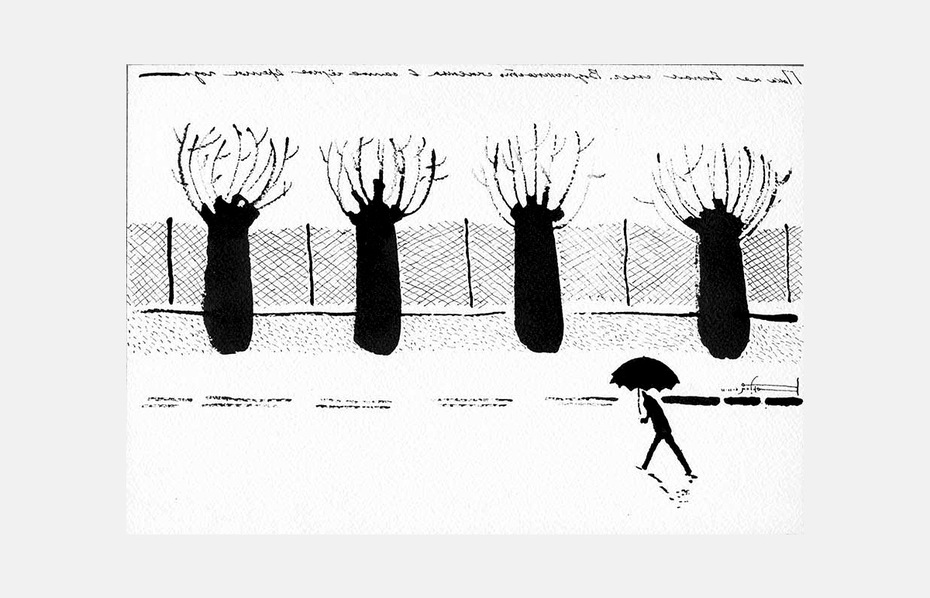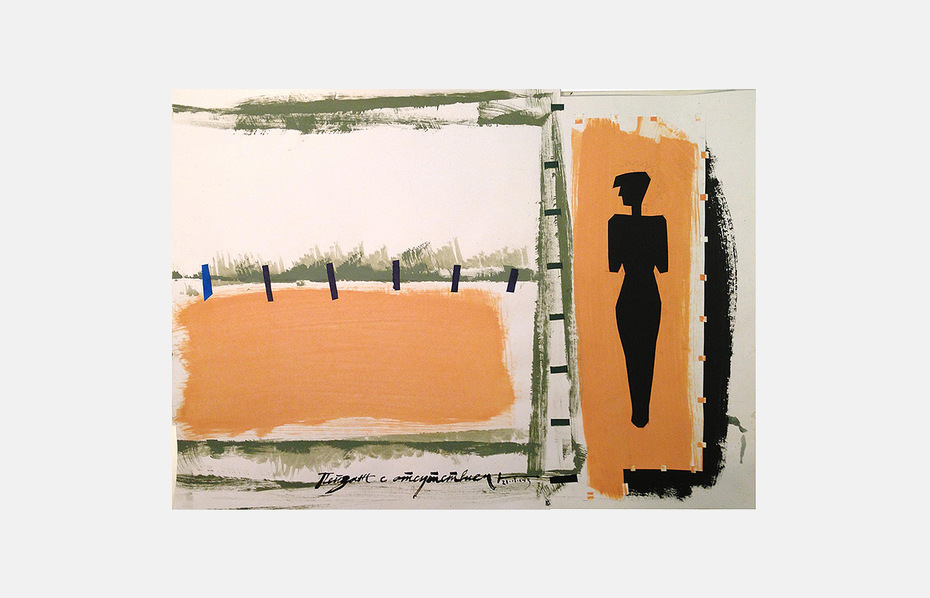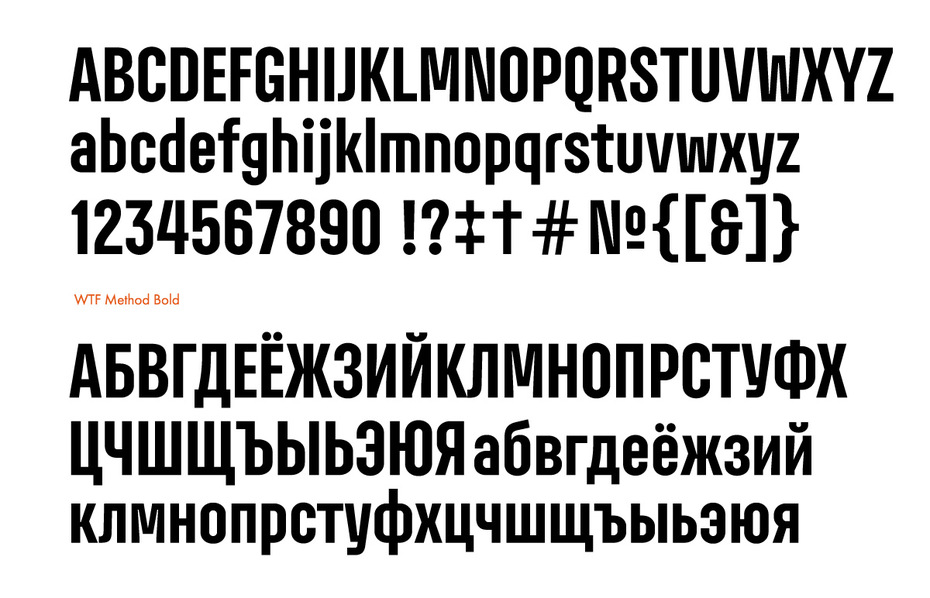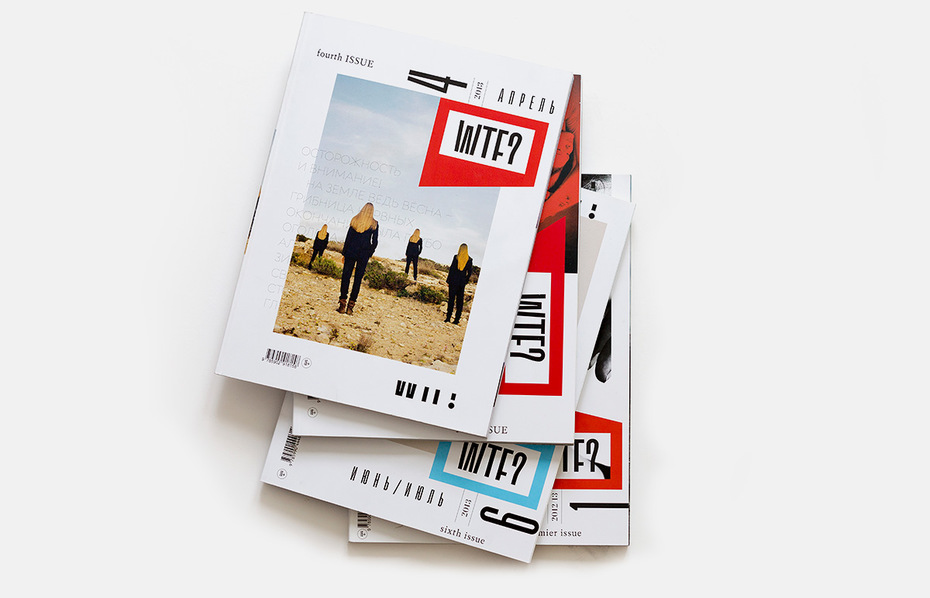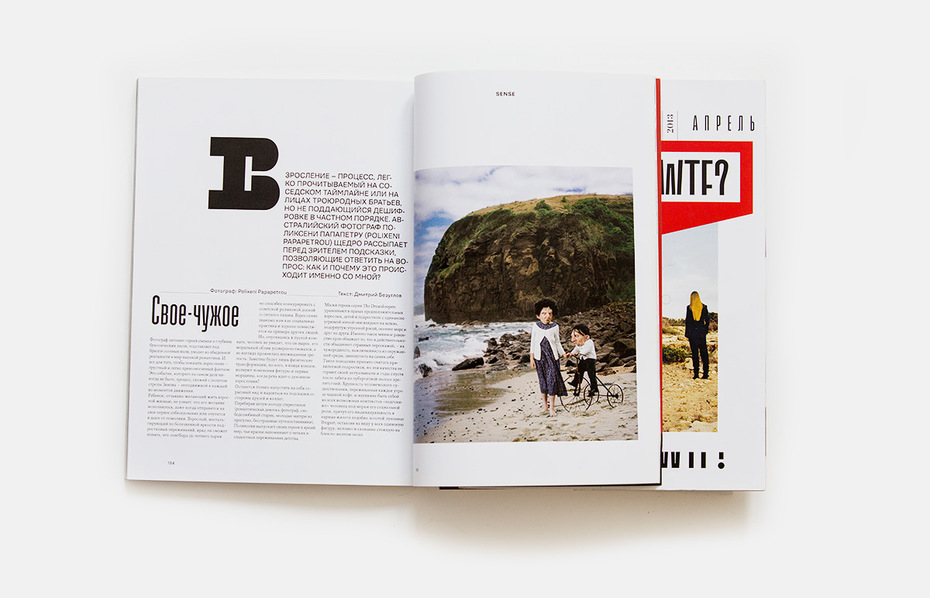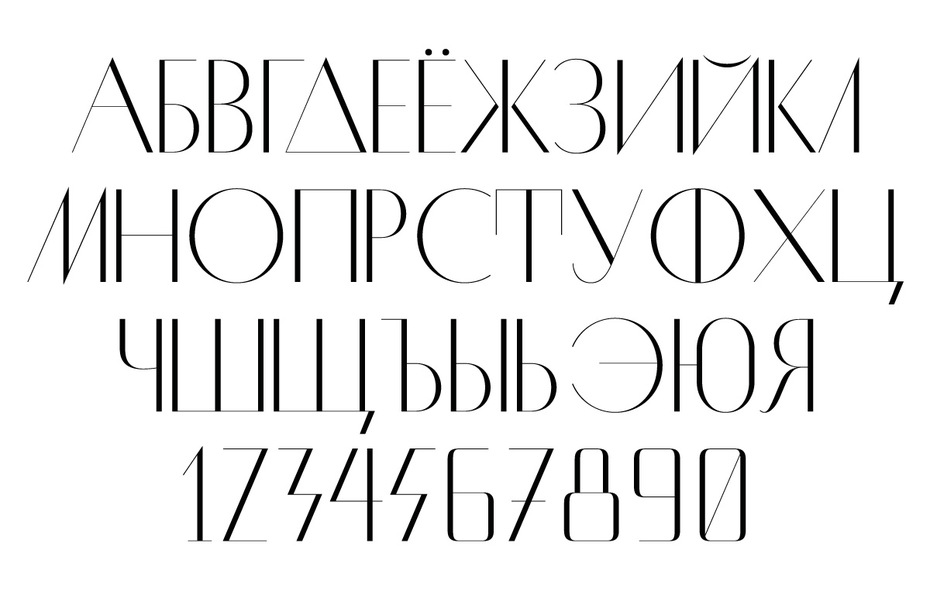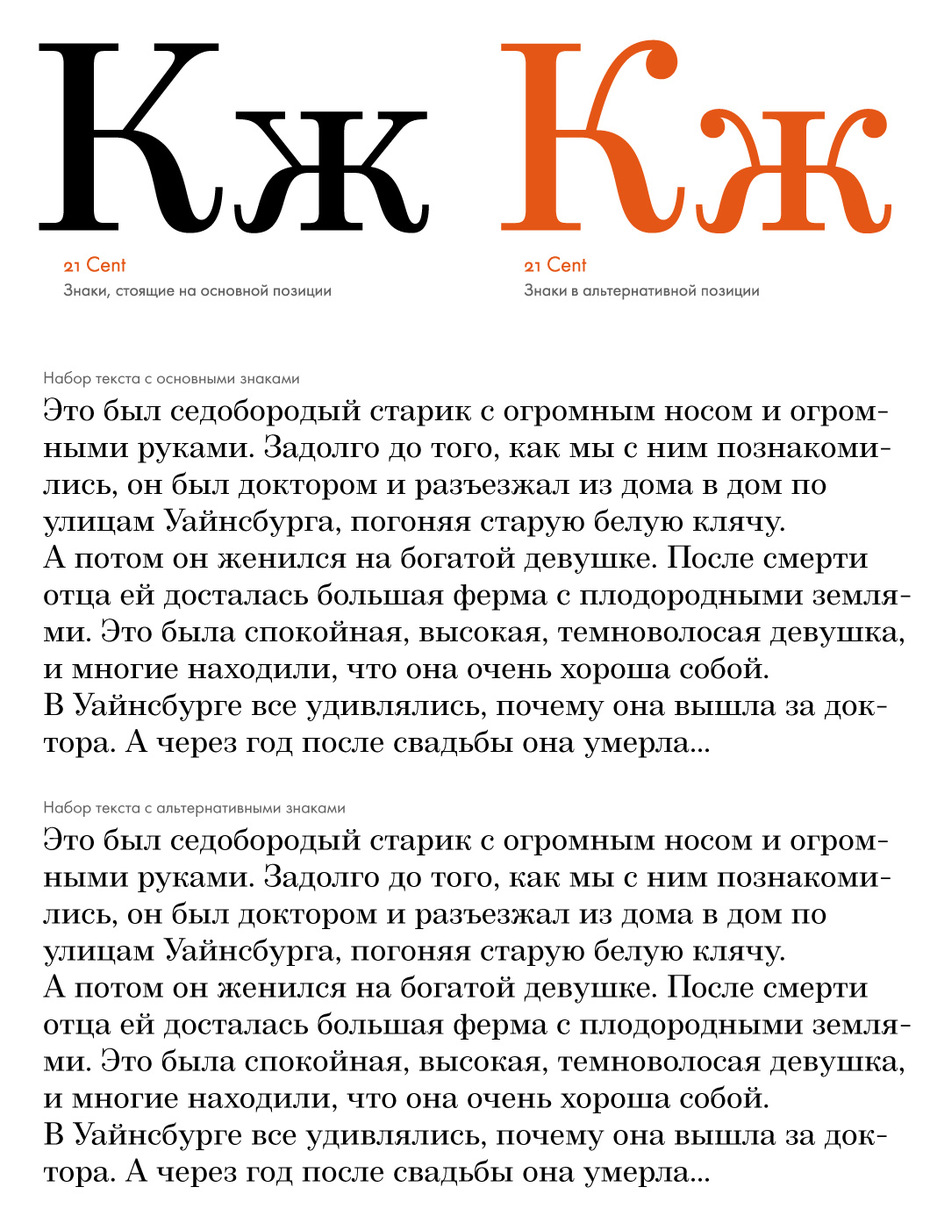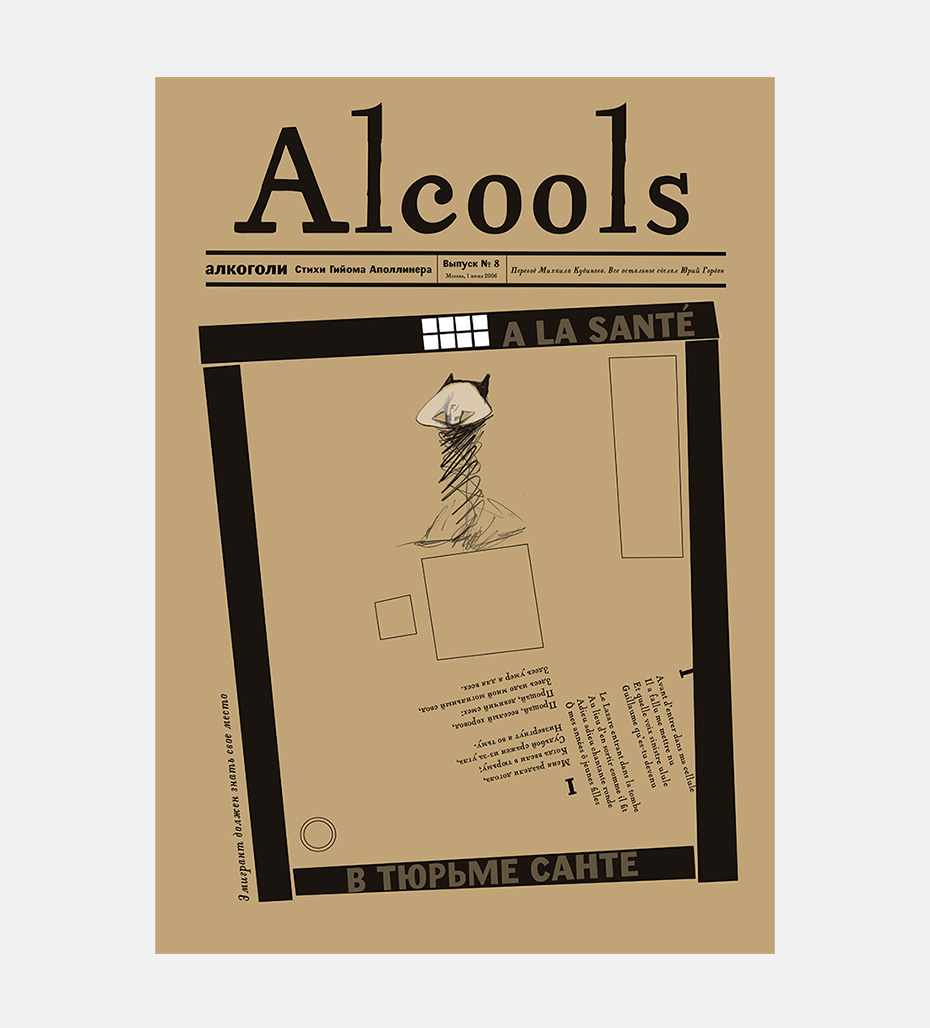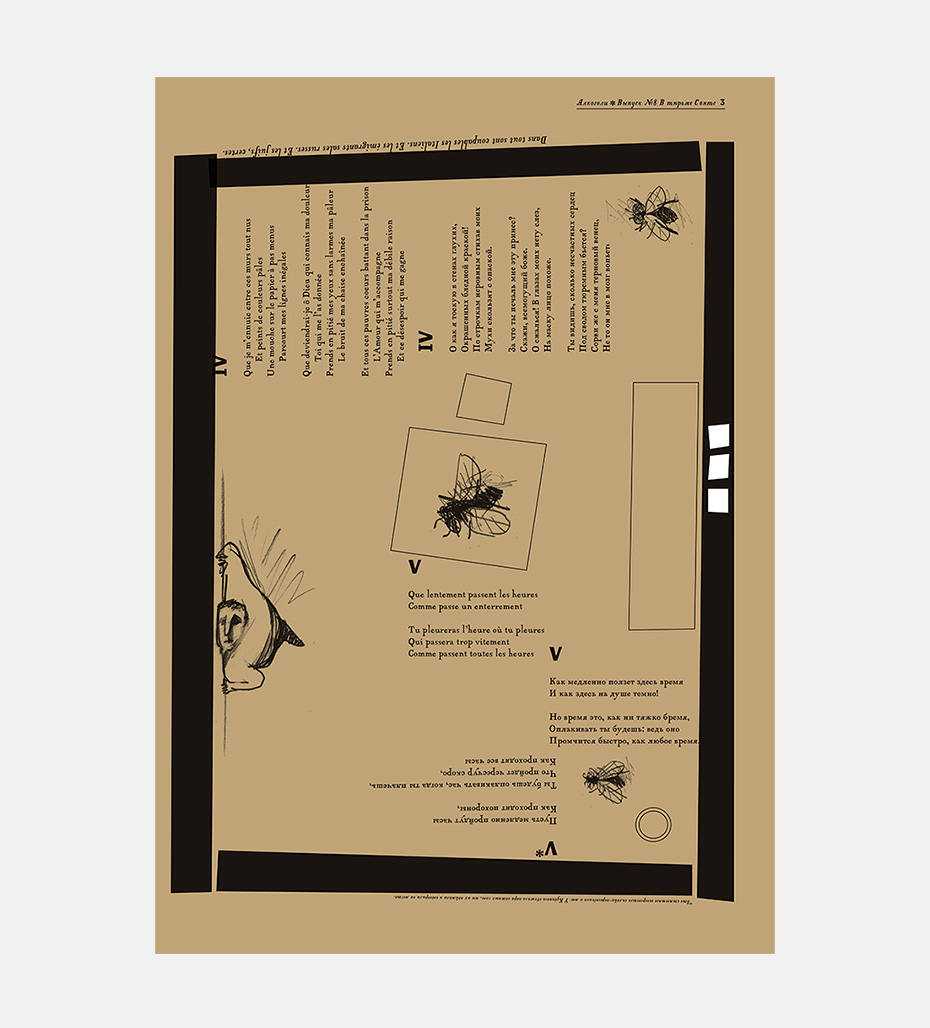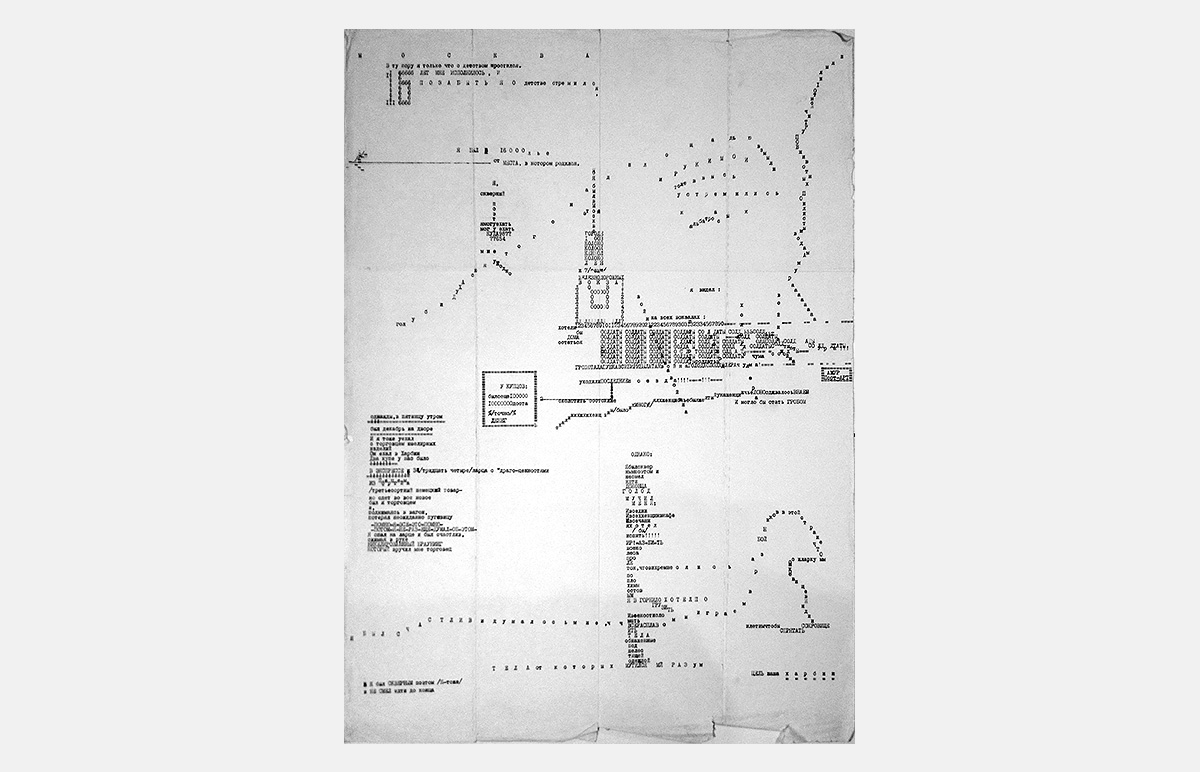
Самая маленькая из больших студий
ет­тер­хед — преж­де все­го сту­дия гра­фи­че­ско­го ди­зай­на, но от­ли­ча­ет­ся она тем, что по­чти во всех про­ек­тах ис­поль­зу­ет шриф­ты из соб­ствен­ной биб­лио­те­ки. А если под­хо­дя­ще­го шриф­та нет, то раз­ра­ба­ты­ва­ет его, ис­хо­дя из по­став­лен­ной за­да­чи. За го­ды ра­бо­ты «натуральное хозяйство» лет­тер­хе­дов об­ре­ло мас­шта­бы боль­шой шриф­то­вой биб­лио­те­ки с гар­ни­ту­ра­ми са­мых раз­лич­ных жан­ров — от ­ак­ци­дент­ных до тек­сто­вых. Хо­те­ли они то­го или нет, но Юрий Гор­дон и Ва­ле­рий Го­лы­жен­ков (не за­бу­дем так­же Оль­гу Ва­силь­ко­ву и Ил­ла­ри­о­на Гор­до­на) по­да­ли при­мер то­го, как при по­мо­щи до­ступ­ных всем тех­но­ло­гий мож­но со­здать яс­ный и уз­на­ва­е­мый ти­по­гра­фи­че­ский стиль, вби­ра­ю­щий в се­бя как тра­ди­ци­он­ные чер­ты, так и аб­со­лют­но но­ва­тор­ские об­ра­зы. И не толь­ко в об­ла­сти шриф­та, как мож­но убе­дить­ся, про­чи­тав ин­тер­вью.
Не­дав­но мы с удив­ле­ни­ем об­на­ру­жи­ли, что да­ле­ко не все рос­сий­ские гра­фи­че­ские ди­зай­не­ры зна­ют о сту­дии Letterhead. Это стран­но для та­ких ста­ро­жи­лов, да­же, мож­но ска­зать, пи­о­не­ров, как вы.
Ва­ле­рий Го­лы­жен­ков: А что в этом уди­ви­тель­но­го? Сей­час ин­фор­ма­ци­он­ный по­ток о ди­зай­не на­столь­ко ве­лик, что ед­ва хва­та­ет сил, что­бы сле­дить за те­ми, кто ра­бо­та­ет ря­дом с то­бой. Год прош­лый, год бу­ду­щий — вот вре­мен­ные рам­ки ди­зай­нер­ской па­мя­ти се­го­дня.
Юрий Гор­дон: Но ко­гда че­ло­век за­ка­зы­ва­ет ди­зайн, мар­ка всё рав­но важ­на. Кли­ен­ты-то зна­ют, к ко­му об­ра­ща­ют­ся и ко­го ре­ко­мен­ду­ют друг дру­гу. Но это от­дель­ный мир, ко­то­рый не пе­ре­се­ка­ет­ся с тем, о ко­то­ром мы го­во­рим.
Ва­ле­рий: Я дол­жен ска­зать, что и мы ма­ло что зна­ем. Но­вые ди­зайн-сту­дии, ге­рои, име­на — это нуж­но по­сто­ян­но от­сле­жи­вать, а еди­но­го ис­точ­ни­ка ин­фор­ма­ции, ко­то­рый бы и фор­ми­ро­вал сре­ду, и ин­фор­ми­ро­вал её, не су­ще­ству­ет. Что-то на­хо­дишь в фейс­бу­ке, что-то поз­во­ля­ет ви­деть пре­по­да­ва­тель­ская ра­бо­та... Прав­да, всё ча­ще хо­чет­ся не ис­кать но­во­го, а, на­про­тив, убе­речь­ся от шква­ла ин­фор­ма­ции, за­крыть­ся и знать как мож­но мень­ше.
По­лу­ча­ет­ся, что вид­ны и за­мет­ны се­го­дня те, кто гром­че осталь­ных, те, кто уме­ет со­зда­вать во­круг се­бя ин­фор­ма­ци­он­ную вол­ну. Это зна­чит для прак­ти­ку­ю­ще­го ди­зай­не­ра, что нуж­но по­сто­ян­но быть в фор­ме, на ви­ду?
Ва­ле­рий: Я ду­маю, что че­ло­век, до­стиг­ший вер­ши­ны в своём де­ле, по­доб­но вос­точ­ной тра­ди­ции, дол­жен за­бы­вать своё имя, брать дру­гое и на­чи­нать всё с ну­ля в но­вом сти­ле. Если он вдруг чув­ству­ет, что на­хо­дит­ся на вер­ши­не, в «то­пе», то дол­жен во­вре­мя со все­ми по­про­щать­ся, об­нять­ся и ска­зать: всё, ре­бя­та, до сви­да­ния. Ко­неч­но, в ди­зай­не все­гда есть свой «Рол­линг Сто­унз». Да, на За­па­де мож­но най­ти ин­те­рес­ных лю­дей и их про­ек­ты. И да­же уди­ви­тель­но, что эти лю­ди по-преж­не­му вы­да­ют со­вре­мен­ный про­дукт, со­звуч­ный на­стро­е­ни­ям, тен­ден­ци­ям. Про­дукт, ко­то­рый на­хо­дит от­клик.
Кто для вас «Рол­линг Сто­унз» в гра­фи­че­ском ди­зай­не?
Юрий: Emigre, ко­неч­но, осо­бен­но в пер­вое вре­мя. До это­го был Не­вилл Бро­уди. Он, по­жа­луй, един­ствен­ный, кто ме­ня в ди­зай­не за­це­пил, не счи­тая «Эми­гре», ко­то­рые при­вле­ка­ли боль­ше с идео­ло­ги­че­ских по­зи­ций: лю­ди де­ла­ли то, что я бы хо­тел де­лать сам. Вы­яс­ни­лось, что они это де­ла­ли, пред­по­ло­жим, на пять лет рань­ше. Бы­ло очень обид­но. Но для ме­ня ди­зайн ни­ко­гда не был ко­неч­ной оста­нов­кой, это был не­кий про­ме­жу­точ­ный этап. Так же, как и ти­по­гра­фи­ка. Но «Эми­гре» все­гда бы­ли те­ми, кто очень ра­до­вал, по­то­му что они за­ни­ма­лись ве­ща­ми бо­лее ши­ро­ки­ми, чем ди­зайн в чи­стом ви­де. Они пе­ре­да­ва­ли ав­тор­ское со­об­ще­ние. Как это на­зы­ва­ет­ся — ди­зайн или чи­стое ис­кус­ство, — не име­ет ни­ка­ко­го зна­че­ния.
Юрий, ваш про­ект Alcools мож­но вос­при­ни­мать как свое­об­раз­ную ре­ак­цию на ра­бо­ты Emigre?
Юрий: Нет, «Ал­ко­го­ли» во­об­ще с этим ни­как не свя­за­ны. Они по­яви­лись де­сять лет на­зад, в 2005 и 2006 го­дах. «Ал­ко­го­ли» свя­за­ны с тем, что я Апол­ли­не­ра знал на­из­усть ещё при­мер­но с шест­на­дца­ти лет. Рань­ше, чем Ман­дель­шта­ма. Ма­ма ра­бо­та­ла в Ака­де­мии на­ук, и я чи­тал лит­па­мят­ни­ки, а в них бы­ла вся фран­цуз­ская по­э­зия XX ве­ка: Апол­ли­нер, Сан­драр, Элю­ар и про­чие ре­бя­та, и я их про­чи­тал как бы за­ра­нее. А по­том уже чи­тал Ман­дель­шта­ма, Па­стер­на­ка и всё осталь­ное. И ко­гда ме­ня при­гла­сил Ми­ша По­гар­ский сде­лать ка­кую-ни­будь кни­гу ху­дож­ни­ка, к это­му мо­мен­ту у ме­ня уже был ди­плом про Сан­дра­ра — «Про­за Транс­си­бир­ско­го экс­прес­са». Он пред­ло­жил сде­лать ка­кую-ни­будь «штуч­ку» про Апол­ли­не­ра.
«Штуч­ки» мне бы­ло ма­ло, по­то­му что я хо­тел сде­лать книж­ку. Но и про­сто книж­ки мне бы­ло ма­ло. И я при­ду­мал ле­ген­ду про па­риж­ско­го под­ма­сте­рье у на­бор­щи­ка, ко­то­рый вы­ре­зал шрифт под на­зва­ни­ем Ко­стро, что­бы для сво­е­го дру­га Виль­гель­ма Апол­ли­на­рия Ко­стро­виц­ко­го сде­лать книж­ку. Я его на­ри­со­вал в «Пей­н­те­ре», за­тем пе­ре­та­щил в «Фонтлаб».
Это со­вер­шен­но не про ди­зайн, а про то, как рас­ска­зы­вать ис­то­рии. Я был и ав­тор, по­то­му что там не толь­ко тек­сты Апол­ли­не­ра, но и мои тек­сты, и на­бор­щик-вер­сталь­щик, и ав­тор шриф­та, и ав­тор ил­лю­стра­ций, и пе­чат­ник, и ку­рьер. По су­ти, это не бы­ла про­сто кни­га сти­хов, ско­рее диа­лог с Апол­ли­не­ром.
А даль­ше по­тре­бо­ва­лась рас­сыл­ка, 50 эк­зем­пля­ров га­зе­ты рас­сы­ла­лись от Ом­ска до Ба­ден-Ба­де­на под­пис­чи­кам бес­плат­но. Под­пис­чи­ки по­лу­ча­ли но­ме­ра га­зе­ты с уни­каль­ным ди­зай­ном. Это бы­ло, ко­неч­но, очень серьёз­ное для ме­ня ис­пы­та­ние чи­сто фи­зи­че­ски, по­то­му что 2/3 ти­ра­жа ухо­ди­ли в брак. Я пе­ча­таю, прин­тер (А3+ «струй­ник») жуёт, в три ча­са но­чи я став­лю че­ты­ре ли­ста, утром встаю — ужас, всё ис­пор­че­но. Я прин­ци­пи­аль­но пе­ча­тал на бу­ма­ге раз­ных цве­тов и стре­мил­ся, что­бы каж­до­му под­пис­чи­ку при­хо­ди­ли вы­пус­ки раз­ных цве­тов. Они бы­ли се­рые, жёл­тые, си­ние, зелё­ные... А вы­пуск из тюрь­мы Сан­те, был на краф­те, един­ствен­ный от­пе­ча­тан­ный на очень дешёвой бу­ма­ге. По­то­му что тюрь­ма.
Каж­до­му че­ло­ве­ку, ко­то­ро­му я это де­ло по­сы­лал, я де­лал при­пис­ки от ру­ки ка­ран­да­шом ря­дом со сти­ха­ми. Здесь и на­чи­нал­ся раз­го­вор с чи­та­те­лем. Ска­жем, Сла­ви­ну я пи­сал од­но, и он сра­зу счи­ты­вал моё по­сла­ние, а Иго­рю Во­ро­ни­ну, во­до­про­вод­чи­ку с дву­мя выс­ши­ми об­ра­зо­ва­ни­я­ми, я пи­сал что-то со­вер­шен­но дру­гое, что ка­са­лось на­шей с ним друж­бы. Все кар­тин­ки вну­три сде­ла­ны дву­мя спо­со­ба­ми: обыч­ным ро­трин­гов­ским тон­ким ка­ран­да­шом с по­сле­ду­ю­щим силь­ным уве­ли­че­ни­ем, чтоб бы­ло по­хо­же на ли­то­гра­фию, или в век­то­ре, с хо­ду в «Ил­лю­стра­то­ре» без эс­ки­зов.
Как ча­сто вам удаёт­ся по­ра­бо­тать над пер­со­наль­ны­ми про­ек­та­ми? Не пре­уве­ли­че­ни­ем бу­дет ска­зать, что прак­ти­че­ски каж­дый ди­зай­нер име­ет меч­ту вы­кро­ить вре­мя и на­ко­нец со­здать что-то «стoя­щее, не­под­власт­ное вре­ме­ни и вли­я­нию за­каз­чи­ка». Та­кой акт чи­сто­го твор­че­ства, ко­то­рый на по­вер­ку мо­жет ока­зать­ся и ил­лю­зи­ей.
Ва­ле­рий: Та­кие про­ек­ты не воз­ни­ка­ют из воз­ду­ха. Ты ста­вишь се­бе за­да­чу сам, но при этом к ней мг­но­вен­но при­тя­ги­ва­ют­ся не­ко­то­рые об­сто­я­тель­ства. «Пред­по­ла­га­е­мые об­сто­я­тель­ства», как у Ста­ни­слав­ско­го. Сво­им сту­ден­там я го­во­рю: по­ка­жи­те, что у вас есть шрифт, так, что­бы вам по­ве­ри­ли. Для на­ча­ла до­ста­точ­но не­сколь­ких букв, на­ри­со­ван­ных в «Ил­лю­стра­то­ре», и ре­аль­ный ди­зайн-про­ект, где эти бук­вы ра­бо­та­ют. И всё, мож­но счи­тать, что шрифт уже су­ще­ству­ет, его идея ове­ще­ствле­на.
Юрий: Я бы хо­тел упо­мя­нуть ве­ли­ко­леп­ный про­ект Ва­ле­ры Garbage Type Foundry, аб­со­лют­но су­ма­сшед­ший. Очень тон­ко сде­лан­ная вещь, до­стой­ная ме­ста на пол­ке ря­дом с кни­га­ми фу­ту­ри­стов. Это та­кая про­во­ка­тив­ная не­боль­шая ве­щи­ца на не­сколь­ко раз­во­ро­тов раз­ме­ром с по­что­вую от­крыт­ку, на стра­ни­цах ко­то­рой со­бра­ны ком­по­зи­ции из «от­хо­дов» шриф­то­вой де­я­тель­но­сти. Та­кая де­кон­струк­ция при­выч­ных шриф­то­вых форм, свое­об­раз­ный шриф­то­вой ка­та­лог из 22 шриф­тов. Ка­жет­ся, у нас оста­лась все­го па­ра эк­зем­пля­ров.
Если счи­тать с осно­ва­ния Letterhead, c 1998 го­да, вам до­ве­лось по­ра­бо­тать над ши­ро­ким спек­тром за­дач. Что бы вы обо­зна­чи­ли основ­ным сво­им до­сти­же­ни­ем?
Юрий: Ма­стер­ство. В ка­кой-то мо­мент я и прав­да на­чал ощу­щать се­бя ма­сте­ром, как бы на­гло это ни зву­ча­ло. Се­го­дня я точ­но знаю, чем от­ли­ча­ет­ся ма­стер от хо­ро­ше­го ди­зай­не­ра или хо­ро­ше­го двор­ни­ка. Де­ло в от­но­ше­нии к за­да­че: на­чи­ная ра­бо­ту, ты по­ни­ма­ешь, что ни­че­го не­воз­мож­но­го нет. Вот нет ни­че­го не­ре­ша­е­мо­го! Прав­да, это не озна­ча­ет, что боль­ше не нуж­но ни у ко­го ни­че­му учить­ся. Ина­че мож­но и с про­фес­си­ей по­про­щать­ся.
Ва­ле­рий: С та­кой по­зи­ции соб­ствен­ное не­со­вер­шен­ство по­ни­ма­ешь аб­со­лют­но от­чётли­во. Да, я не умею де­лать три чет­вер­ти то­го, что уме­ют дру­гие лю­ди. Но я знаю, что у ме­ня есть свой путь, вла­дею на­вы­ка­ми, при по­мо­щи ко­то­рых я сде­лаю лю­бую ра­бо­ту. Что бы ни слу­чи­лось, я справ­люсь. Об этом го­во­рит Юра. То есть речь про по­зна­ние, по­ни­ма­ние се­бя и про очень трез­вую оцен­ку соб­ствен­ных сил. При этом ко­ли­че­ство за­дач не умень­ша­ет­ся — оно уве­ли­чи­ва­ет­ся в гео­мет­ри­че­ской про­грес­сии.
Юрий: Это точ­ное за­ме­ча­ние. Рань­ше до­ста­точ­но бы­ло те­бя са­мо­го. И ты как бы ви­дел свой пре­дел. Сей­час по­ни­ма­ешь, что мо­жешь сде­лать боль­ше и хо­ро­шо бы иметь в рас­по­ря­же­нии двух-трёх те­бя.
Ва­ле­рий: Да, причём ни­ко­му дру­го­му нет же­ла­ния до­ве­рять ту или иную за­да­чу, да­же учи­ты­вая, что ре­зуль­та­ты-то мо­гут быть и луч­ше, и воз­ник­нет да­же рев­ность к этим ре­зуль­та­там. Но во­об­ще-то друг дру­га мы по­ни­ма­ем и мо­жем до­ве­рить­ся. От­сю­да и кон­сер­ва­тив­ный под­ход к рас­ши­ре­нию сту­дии.
Юрий: Не кон­сер­ва­тив­ный, а за­кон­сер­ви­ро­ван­ный! Мы са­мая ма­лень­кая из боль­ших сту­дий — это моя лю­би­мая фра­за. Боль­ше пя­ти че­ло­век у нас ни­ко­гда не ра­бо­та­ло. Сей­час трое, и не за­бы­вай­те про Оль­гу Ва­силь­ко­ву, ко­то­рая иг­ра­ет огром­ную роль. В мо­мент, ко­гда ни­че­го не хо­чет­ся де­лать, всё ка­жет­ся ужас­ным, — я мо­гу отой­ти на шаг в сто­ро­ну, и кто-то из них дво­их под­хва­тит ра­бо­ту и про­дол­жит с то­го ме­ста, где я оста­но­вил­ся. Ху­же не бу­дет точ­но. Это очень важ­ная ис­то­рия.
Вы ак­тив­но ра­бо­та­е­те на ме­диа­рын­ке. Сре­ди ва­ших за­каз­чи­ков мно­го арт-ди­рек­то­ров жур­на­лов. Для ди­зай­не­ра шриф­та это один из ин­те­рес­ных и бла­го­при­ят­ных фор­ма­тов со­труд­ни­че­ства. Опыт ка­ких про­ек­тов вам осо­бен­но це­нен?
Ва­ле­рий: Из не­дав­них про­ек­тов я бы упо­мя­нул жур­нал «Де­ло­вой квар­тал» и What’s the fashion?. У пер­во­го бы­ли ам­би­ции фе­де­раль­но­го из­да­ния уров­ня «Ком­мер­сан­та», но к мо­мен­ту сда­чи в си­лу раз­ных при­чин, так ска­зать, не­пре­одо­ли­мой си­лы они не­сколь­ко по­уга­сли. Вто­рой жур­нал то­же, к со­жа­ле­нию, пре­кра­тил своё су­ще­ство­ва­ние.
WTF? за­ка­зы­ва­ли ма­кет, зная, что мы за­ни­ма­ем­ся и шриф­та­ми. Ра­зу­ме­ет­ся, я, как раз­ра­бот­чик ма­ке­та, мог са­мо­му се­бе за­ка­зать и шриф­ты, а за­од­но и про­ве­рить, как они бу­дут ра­бо­тать в ма­ке­те. Арт-ди­рек­ция и ре­дак­ция жур­на­ла толь­ко под­дер­жа­ли нас в этом. Пи­лот­ные вы­пус­ки ме­ня по­ра­до­ва­ли: ма­кет ра­бо­тал, ди­зай­не­ры на­хо­ди­ли про­стран­ство для экс­пе­ри­мен­тов, они ком­би­ни­ро­ва­ли на­чер­та­ния шриф­тов. Од­на­ко со вре­ме­нем ма­кет и шриф­ты ста­ли вы­ра­ба­ты­вать­ся. Мы об­су­жда­ли, как мож­но осве­жить из­да­ние, до­ба­вив что-то в ма­кет. Но ре­дак­ция по­шла даль­ше: сме­ни­ла кон­цеп­цию из­да­ния и про­ве­ла ре­ди­зайн.
Юрий: Но во­об­ще нам все­гда вез­ло. Арт-ди­рек­то­ра раз­ные, но каж­дый по-сво­е­му был пре­кра­сен. Аня Жа­ке­вич (на тот мо­мент арт-ди­рек­тор Vogue), на­при­мер, все­гда точ­но зна­ла, что нуж­но, спо­ри­ла с на­ми, по­прав­ля­ла каж­дую бук­ву. И это бы­ло здо­ро­во, по­то­му что ре­зуль­тат по­лу­чал­ся точ­нее, чем если бы мы всё взя­ли на се­бя. И со­вер­шен­но по-дру­го­му стро­и­лась ра­бо­та с Ди­мой Бар­ба­не­лем (Ма­стер­ская Бар­ба­не­ля) и Мак­си­мом Ни­ка­но­ро­вым (Esquire). С ни­ми был сов­мест­ный по­иск, по­то­му что ни­кто не знал, что в ито­ге по­лу­чит­ся. Я рас­ска­зы­вал, что Бар­ба­нель как-то при­слал фо­то­гра­фию ав­то­мо­би­ля «Вольво» 70-х го­дов вы­пус­ка с прось­бой сде­лать шрифт, по­хо­жий на эту ма­ши­ну. А я — пол­ный ноль в ав­то­про­ме. Вот и пля­ши.
Ва­ле­рий: Воз­вра­ща­ясь к те­ме ма­стер­ства: ма­сте­ру же­ла­тель­но уметь пе­ре­бо­роть пер­вое же­ла­ние ска­зать «нет» на за­ме­ча­ние или прось­бу арт-ди­рек­то­ра и дать се­бе труд по­ду­мать, как мож­но дви­нуть­ся даль­ше и учесть это за­ме­ча­ние. Это хо­ро­ший опыт.
Юрий: Ко­неч­но. Ко­гда арт-ди­рек­тор точ­но по­ни­ма­ет, что ему нуж­но, яс­но пред­став­ля­ет ре­зуль­тат, для те­бя это воз­мож­ность рас­сла­бить­ся. И если по­на­ча­лу я спо­рил с Аней (по­мню, у нас бы­ли раз­но­гла­сия по по­во­ду хво­сти­ка у кур­сив­но­го Ц), то со вре­ме­нем до­ве­рил­ся ей.
В своё вре­мя вы сде­ла­ли не­ма­ло ки­рил­ли­за­ций для са­мых раз­ных жур­на­лов. Как сей­час об­сто­ит де­ло с пе­ре­во­да­ми шриф­тов?
Юрий: По­жа­луй, те­перь это не к нам. Мы пе­ре­ста­ли за­ни­мать­ся пе­ре­во­да­ми, по­те­ря­ли ин­те­рес. Да, ко­гда мы за­ни­ма­лись шриф­та­ми для рус­ско­го Rolling Stone, то­гда бы­ло ин­те­рес­но.
Ва­ле­рий: Лю­бо­пыт­но, что обыч­но рус­ские ре­дак­ции не бы­ли огра­ни­че­ны жёст­ки­ми тре­бо­ва­ни­я­ми от­но­си­тель­но шриф­тов. По­чти ни­кто не обя­зы­вал арт-ди­рек­то­ра рус­ско­го из­да­ния на­би­рать жур­нал те­ми же шриф­та­ми, ко­то­рые ис­поль­зу­ют­ся в ори­ги­на­ле. От них жда­ли толь­ко ма­ке­та на со­гла­со­ва­ние. Ино­гда мог­ли что-то по­ре­ко­мен­до­вать, но не бо­лее.
Ва­ле­рий Го­лы­жен­ков в сту­дии. Моск­ва, 2016. Фо­то — Тим По­кри­чук.
Юрий: И арт-ди­рек­то­ра не хо­тят уда­рить ли­цом в грязь.
Ва­ле­рий: На­при­мер, в рус­ском из­да­нии «Во­га» мы боль­ше об­су­жда­ли ма­ке­ты за­пад­ных «Во­гов», чем шриф­ты. Речь шла о том, что­бы ти­по­гра­фи­ка рус­ско­го жур­на­ла бы­ла не ху­же ита­льян­ско­го, фран­цуз­ско­го. Не ска­жу, что их ти­по­гра­фи­ка ме­ня впе­чат­ли­ла, я бы кое-что и по­пра­вил там, но впе­чат­ле­ние от букв, от их ви­зу­аль­но­го ис­пол­не­ния бы­ло силь­ным. Вот это в ито­ге за­хо­те­лось по­вто­рить.
Юрий: Я ду­маю, сей­час арт-ди­рек­то­ра ста­ли ина­че смот­реть на ве­щи. Рань­ше лю­ди не мог­ли пред­ста­вить, что в Рос­сии кто-то спо­со­бен сде­лать шрифт на вы­со­ком уров­не. Се­го­дня всё из­ме­ни­лось: за­каз­чик по­ни­ма­ет, что мы сде­ла­ем ки­рил­ли­цу с тем вку­сом, ко­то­рый за­пад­ные лю­ди не чув­ству­ют. И по­это­му всё ча­ще об­ра­ща­ют­ся к нам, или не к нам, в об­щем, к тем, кто уме­ет.
Ва­ле­рий: Удач­ных за­пус­ков жур­на­лов сей­час край­не ма­ло. Я имею в ви­ду, та­ких жур­на­лов, где ти­по­гра­фи­ка внят­ная, а шриф­ты ка­че­ствен­ные. Ну не вы­хо­дит у ме­ня вос­при­ни­мать как со­бы­тие, на­при­мер, вы­ход жур­на­ла с пло­хи­ми шриф­та­ми вну­три.
Юрий: За пло­хи­ми шриф­та­ми бу­ду­щее! Это от­дель­ный раз­го­вор.
Ва­ле­рий: 5–7 лет на­зад я с ин­те­ре­сом под­хо­дил к жур­наль­но­му ки­ос­ку. Се­го­дня мне не­ин­те­рес­но. Мне ка­жет­ся, для жур­на­ла важ­на цель­ность вы­ска­зы­ва­ния. Или возь­мём Numero, ко­то­рый решён Гель­ве­ти­кой в ори­ги­на­ле. Ты смот­ришь и ду­ма­ешь: ка­кая же нуж­на твёр­дая уве­рен­ность, что­бы и рус­ское из­да­ние на­брать Гель­ве­ти­кой. Я мо­гу вос­при­нять это как ху­до­же­ствен­ный жест, но жест стран­ный. Я всё вре­мя спо­ты­ка­юсь об эту вер­сию Гель­ве­ти­ки! Воз­мож­но, будь там Праг­ма­ти­ка, всё вы­гля­де­ло бы по­чи­ще, ней­траль­нее, и этот шрифт ра­бо­тал бы, под­дер­жи­вая кон­цеп­цию жур­на­ла.
Са­мо сло­во­со­че­та­ние «жур­наль­ный ки­оск» уже вос­при­ни­ма­ет­ся как ар­ха­изм, а на этом фо­не ещё и наш ры­нок по­ки­да­ют (не без по­ли­ти­че­ско­го дав­ле­ния) меж­ду­на­род­ные из­да­те­ли. Ухо­дит «бу­ма­га» ведь. А про кни­ги и во­все го­во­рить не при­хо­дит­ся: ти­ра­жи ста­ли у всех ми­кро­ско­пи­че­ские.
Ва­ле­рий: Ка­кие-то ве­щи всё-та­ки хо­чет­ся дер­жать в ру­ках, а не толь­ко раз­гля­ды­вать с экра­на. Вы за­ме­ти­ли, что мы ча­сто лю­бу­ем­ся wood type про­ек­та­ми, ме­тал­ли­че­ским на­бо­ром, вы­со­кой пе­ча­тью. Мы ви­дим, как эн­ту­зи­а­сты вос­ста­нав­ли­ва­ют стан­ки, пе­ча­та­ют на бу­ма­ге руч­но­го ли­тья...
Юрий Гор­дон в сту­дии. Моск­ва, 2016. Фо­то — Тим По­кри­чук.
Юрий: Ве­ро­ят­но, бу­маж­ные из­да­ния та­ко­го ро­да бу­дут при­ви­ле­ги­ей ав­то­ра и его не­боль­шо­го кру­га под­пис­чи­ков. Это ис­то­рия про ни­шу, ко­то­рая мне ка­жет­ся очень важ­ной в со­вре­мен­ном ми­ре, ни­шу для лю­бо­го ав­тор­ско­го тру­да. Я как-то услы­шал про швей­цар­ско­го пи­са­те­ля (не по­мню его име­ни), он пи­шет ро­ма­ны, и у не­го при­мер­но ты­ся­ча под­пис­чи­ков. Каж­дый но­вый ро­ман эти под­пис­чи­ки мг­но­вен­но рас­ку­па­ют. Сде­лал, про­дал, и всё — боль­ше ни­ко­му не до­ста­лось. Я бы мог за­нять­ся при­мер­но тем же, если за­кон­чат­ся за­ка­зы на ди­зайн. И я точ­но знаю, что моя ауди­то­рия из двух­сот, услов­но го­во­ря, че­ло­век ку­пит но­вый шрифт, или книж­ку, или кар­ту. Я не ду­маю о мо­де, про­сто де­лаю то, что мне нра­вит­ся. И при опре­делён­ных об­сто­я­тель­ствах эта ни­ша мо­жет стать очень по­пу­ляр­ной, все­мир­но из­вест­ной, по­че­му бы и нет.
Юрий, по­ми­мо «Лет­тер­хе­да», ва­ши ра­бо­ты пред­став­ле­ны на пер­со­наль­ном сай­те. Оче­вид­но, вы го­во­ри­те имен­но о та­кой ни­ше?
Юрий: Во­об­ра­зи­те се­бе че­ло­ве­ка, ко­то­ро­го зна­ют в раз­ных ли­цах: кто-то прочёл его книж­ку, кто-то уви­дел кар­тин­ку, им на­ри­со­ван­ную, кто-то шрифт, кто-то жур­нал, оформ­лен­ный им. Че­ло­век рас­сы­пан, и раз­ные груп­пы лю­дей, ко­то­рые с ним об­ща­ют­ся, ни­как не со­еди­не­ны вме­сте. На своём сай­те я по­пы­тал­ся со­брать это­го че­ло­ве­ка во­еди­но. Мне хо­те­лось до­не­сти до лю­дей, что мои шриф­ты, кар­тин­ки, тек­сты — всё это ча­сти од­но­го про­ек­та!
Воз­вра­ща­ясь к про­фес­сии ди­зай­не­ра шриф­та. На ва­шей па­мя­ти она пре­тер­пе­ла (с тех­но­ло­ги­че­ской точ­ки зре­ния) ра­ди­каль­ные транс­фор­ма­ции. Что нас ждёт в бу­ду­щем?
Юрий: Ждём при­ше­ствия но­во­го Гу­тен­бер­га, как ска­зал Ва­ле­ра. Да­вай­те чест­но при­зна­ем­ся се­бе, что в бу­ду­щем лю­бой ува­жа­ю­щий се­бя арт-ди­рек­тор смо­жет, по­тя­нув за 2–3 ры­ча­га, лег­ко на­стро­ить се­бе шрифт. И это бу­дет пра­виль­ная ис­то­рия. А ещё бо­лее пра­виль­ная ис­то­рия за­клю­ча­ет­ся в том, что и лю­бой поль­зо­ва­тель, по­тя­нув за 2–3 ры­ча­га, смо­жет на­стро­ить се­бе шрифт. Я не го­во­рю со­здать шрифт, ни­кто не от­ме­нит про­фес­сию шриф­то­ви­ка, упа­си бо­же! Про­сто у каж­до­го че­ло­ве­ка бу­дет свой шриф­то­вой Garage Band. Ко­то­рый, за­ме­чу, не сде­лал всех Мо­цар­та­ми и Ба­ха­ми. На­ша уз­ко­спе­ци­аль­ная, не­ве­ро­ят­но кла­но­вая, пря­мо-та­ки мо­на­ше­ская про­фес­сия мо­жет рас­крыть­ся, стать по­пу­ляр­ным и страш­но ин­те­рес­ным за­ня­ти­ем.
Ва­ле­рий: Это уже про­ис­хо­дит. Школ шриф­та сколь­ко от­кры­лось: в Пи­те­ре три-че­ты­ре, две в Моск­ве... Зав­тра я ре­шу от­крыть шко­лу, по­сле­зав­тра ещё ка­кие-ни­будь ре­бя­та. Гра­ни­ца меж­ду гра­фи­че­ским ди­зай­не­ром и шриф­то­ви­ком раз­мы­ва­ет­ся, про­фес­си­о­нал на­чи­на­ет ра­бо­тать и там и там. Вла­ди­мир Ефи­мов го­во­рил, что он кое-что по­ни­ма­ет в бук­вах, но все­гда скром­но от­да­вал се­бе от­чёт в том, что ди­зайн — это дру­гая об­ласть, ко­то­рую он лишь об­слу­жи­ва­ет. Сей­час че­ло­век с опы­том ди­зай­не­ра сме­ло де­ла­ет шрифт.
Юрий: И это слу­чай Гу­тен­бер­га, Гриф­фо, Эль­зе­ви­ров, План­те­на, то есть лю­дей, ко­то­рые мог­ли го­во­рить «мне нуж­но вот это и это». Фак­ти­че­ски, они вы­ра­жа­ли соб­ствен­ную точ­ку зре­ния. Ка­кое-то вре­мя это­го не бы­ло, на­при­мер, Гилл — ско­рее ис­клю­че­ние из пра­вил XVII–XIX ве­ков, он ско­рее ху­дож­ник, чем шриф­то­вик, по­это­му его ме­та­фо­ры ши­ре, а хо­ды силь­нее, чем у тех, кто за­ни­мал­ся толь­ко бук­ва­ми. Мне ка­жет­ся, сей­час луч­шие шриф­то­вые идеи ге­не­ри­ру­ют­ся вну­три ди­зайн-про­цес­са, в при­гра­нич­ных ди­зай­ну об­ла­стях, да­же в стрит-ар­те, на­при­мер. А в бу­ду­щем всё это долж­но уй­ти в ру­ки поль­зо­ва­те­ля, по­тре­би­те­ля.
Что же бу­дет, по-ва­ше­му, с уров­нем ти­по­гра­фи­ки в этом слу­чае?
Юрий: Он ста­нет вы­ше, ра­зу­ме­ет­ся.
Ва­ле­рий: В элек­трон­ных кни­гах я мо­гу по­ме­нять раз­мер шриф­та, то есть сра­зу от­сту­пить от пра­вил, за­дан­ных ди­зай­не­ром из­да­ния, мо­гу во­об­ще сме­нить шрифт. И та­ких воз­мож­но­стей по на­строй­ке ти­по­гра­фи­ки бу­дет всё боль­ше.
Юрий: У ме­ня есть по­ня­тие «вку­с чте­ния», ко­то­рое не раз­ви­то, не вне­дре­но ни у нас, ни на За­па­де. А ведь это важ­ней­шая шту­ко­ви­на! Мы не ду­ма­ем, ка­кую ка­шу пе­режё­вы­ва­ем, ко­гда «едим» шрифт. Го­во­рят об удо­бо­чи­та­е­мо­сти и про­чем, но вкус чте­ния со­вер­шен­но про дру­гое. Я это по­нял, ко­гда го­то­вил вто­рое из­да­ние «Кни­ги про бук­вы». От дли­тель­но­го чте­ния тек­ста, на­бран­но­го од­ним шриф­том, на­би­ва­ет­ся оско­ми­на, дру­гим — по­вы­ша­ет­ся на­стро­е­ние. Это ведь оче­вид­но, и нуж­но, что­бы кто-то это донёс до пуб­ли­ки! Мы не по­ни­ма­ем са­ми, как чи­та­ем, что с на­ми про­ис­хо­дит в тот мо­мент, ко­гда мы углуб­ля­ем­ся в текст.
То­гда в «Ай­букс» или «Бук­мей­те» нуж­но пред­ла­гать на­стра­и­вать не шриф­ты, а на­стро­е­ния.
Юрий: Ко­неч­но! Это без­ум­но ин­те­рес­ный про­цесс. Я чи­таю гла­мур­ный жур­нал, а на­стро­е­ние у ме­ня сей­час не гла­мур­ное. По­че­му бы не сме­нить это на­стро­е­ние в жур­на­ле? Джойс, на­бран­ный Гель­ве­ти­кой, и Джойс, на­бран­ный Джор­джи­ей, — это два со­вер­шен­но раз­ных тек­ста, по­то­му что один мед­лен­нее, а дру­гой бы­стрее. Это шту­ка, ко­то­рую нуж­но по­нять, причём осмыс­лить её долж­на са­ма пуб­ли­ка. Даль­ше — де­ло тех­ни­ки, ка­кой-ни­будь Apple при­ду­ма­ет, как ме­нять стра­ни­цу под тво­им взгля­дом. Уже есть тех­но­ло­гия, ко­то­рая поз­во­ля­ет ка­ме­ре опре­де­лять ди­стан­цию до глаз.
Не­сколь­ко лет на­зад, рас­су­ждая о бу­ду­щем, вы с эн­ту­зи­аз­мом рас­ска­зы­ва­ли о про­ек­те про­грам­мы «Про­тей», ко­то­рую вы про­ек­ти­ро­ва­ли с Юри­ем Яр­мо­лой. Ка­кие идеи вы ту­да за­кла­ды­ва­ли и ка­ко­ва их судь­ба?
Юрий: «Про­тей» при­снил­ся в день ро­жде­ния, ко­гда мне ис­пол­ни­лось 50. Я уви­дел, как бук­вы ме­ня­ют­ся у ме­ня под ру­ка­ми. Ска­жем, я уби­раю за­сеч­ку в бук­ве, и она ис­че­за­ет во всём шриф­те. О, ка­кая пре­лесть! Где-то пол­го­да с этой иде­ей я жил, по­сле на­пи­сал в ЖЖ в на­де­жде, что это не про­сто дурь ка­кая-то. Ме­ня сна­ча­ла по­зна­ко­ми­ли с Ди­мой Апа­но­ви­чем, по­том по­явил­ся Юра Яр­мо­ла, ко­то­рый ска­зал: «Да­вай де­лать». Мы за­клю­чи­ли фор­маль­ный кон­тракт, и се­го­дня но­вый FontLab ба­зи­ру­ет­ся на гра­фи­че­ском ядре «Про­тея». Ре­бя­та по­пы­та­лись сде­лать «Про­тей» и по­ня­ли, что не по­лу­ча­ет­ся. Вот, пред­по­ло­жим, взять Кон­кве­рор, 54 на­чер­та­ния, это 100 000 за­се­чек. Я хо­чу их од­ним дви­же­ни­ем по­ме­нять, но лю­бой гра­фи­че­ский дви­жок про­сто не вы­дер­жи­ва­ет та­кой на­груз­ки. Пер­вый ва­ри­ант «Про­тея» по­лу­чил­ся очень тор­моз­ным, да­же на уров­не не­сколь­ких букв. Тем не ме­нее моя идея по­лу­чи­ла раз­ви­тие, и сей­час ре­бя­та на­ча­ли при­ду­мы­вать свои функ­ции, ра­бо­ту с кри­вы­ми, ряд тех­но­ло­гий, ко­то­рые Юра по­ка не до­бав­ля­ет в но­вые вер­сии «Фонтла­ба».
Но у нас есть чёт­кое по­ни­ма­ние, что шрифт дол­жен на сто про­цен­тов управ­лять­ся па­ра­мет­ри­че­ски. Про­грам­ма долж­на знать ана­то­мию бук­вы, иметь ва­ри­ан­ты ске­ле­та. По су­ти, «Про­тей» — это тем­плейт, пол­но­стью управ­ля­е­мый ша­блон, в ко­то­ром по за­про­су ав­то­ра ме­ня­ет­ся лю­бая де­таль бук­вы. Это пер­вый уро­вень вза­и­мо­дей­ствия. Вто­рой уро­вень — управ­ле­ние па­ра­мет­ра­ми на сто­ро­не поль­зо­ва­те­ля. Ин­стру­мент в InDesign, на­при­мер. А тре­тий уро­вень — ин­стру­мент в элек­трон­ной кни­ге, в ри­де­ре. Вот век­тор раз­ви­тия «Про­тея». На сто­ро­не раз­ра­бот­чи­ка — пол­ная вер­сия, бо­лее усечён­ный ва­ри­ант у ди­зай­не­ра, а на сто­ро­не поль­зо­ва­те­ля со­всем про­стая вер­сия. Но ра­бо­та­ют они на од­ной тех­но­ло­гии, и та­кая тех­но­ло­гия есть. Про­сто у ре­бят не хва­та­ет ре­сур­сов, что­бы до­ве­сти её до ума, всё-та­ки они не Adobe, нет та­ких мощ­но­стей. Но это нуж­но сде­лать для то­го, что­бы из­ме­ни­лась ра­бо­та со шриф­том в прин­ци­пе!
Се­го­дня, ка­жет­ся, уже до­ста­точ­но «пе­ре­до­вых» тех­но­ло­гий, ко­то­рые поз­во­ля­ют со­зда­вать 50 од­но­тип­ных шриф­тов в день. Раз­ве это не ту­пи­ко­вый путь?
Юрий: Это ещё од­на ис­то­рия, ко­то­рую я хо­тел бы озву­чить. Я счи­таю, что сей­час шриф­то­вое де­ло на­хо­дит­ся на уров­не жи­во­пи­си ака­де­ми­че­ско­го фран­цуз­ско­го са­ло­на 1870-х го­дов. При­мер­но в тот от­ре­зок вре­ме­ни, ко­гда там по­явил­ся Эду­ард Ма­не и все от ужа­са схва­ти­лись за го­ло­ву. Пуб­ли­ка сви­стит, вол­ну­ет­ся, а по­том по­яв­ля­ет­ся Ван Гог. И всё ме­ня­ет­ся окон­ча­тель­но, бес­по­во­рот­но.
Ва­ле­рий: И Ма­не уже ка­жет­ся впол­не нор­маль­ным, здо­ро­вым ху­дож­ни­ком.
Юрий: Я ду­маю, что ти­по­гра­фи­ка за ве­ка сво­е­го су­ще­ство­ва­ния ста­ла слиш­ком хо­ро­ша. Со­вре­мен­ный шрифт — он та­кой чи­стый, та­кой пре­крас­ный. Он нашёл свою мат­ри­цу. Уже всё най­де­но. Ла­ти­ни­ца до­ве­де­на до иде­а­ла, на­чи­ще­на до со­вер­шен­ства уже в XVI ве­ке. Что же даль­ше? Де-кон-струк-ци-я. Раз­ру­ше­ние.
Даль­ше — пре­сло­ву­тый вкус чте­ния, ин­ди­ви­ду­а­ли­зи­ро­ван­ные шриф­ты, не­пра­виль­ность, за­ра­нее за­ло­жен­ные в шрифт ошиб­ки. Долж­на про­изой­ти не­кая ав­то­ри­за­ция шриф­та. Ти­по­граф пе­ре­ста­нет рас­тво­рять­ся в своём шриф­те до пол­но­го ис­чез­но­ве­ния, воз­ник­нет по-на­сто­я­ще­му ав­тор­ская ти­по­гра­фи­ка. И она ухо­дит вниз, в вось­мой кегль.
В этом слу­чае воз­ни­ка­ет дру­гая про­бле­ма. За мно­го ве­ков ра­бо­ты с кни­гой, со шриф­том лю­ди на­учи­лись вос­при­ни­мать опре­делён­ный диа­па­зон форм, счи­ты­вать их. Как лю­ди вос­при­мут ту па­ра­диг­му, о ко­то­рой вы го­во­ри­те?
Юрий: Как воз­ник­ли шко­лы обу­че­ния со­вре­мен­но­му ис­кус­ству? Их не бы­ло, и по­том они по­яви­лись. Пред­по­ло­жим, в 1880 го­ду не бы­ло ни од­ной шко­лы со­вре­мен­но­го ис­кус­ства. Но воз­ник­ли Ба­у­хаус и ВХУ­ТЕ­МАС — на­ту­раль­ные шко­лы с те­о­ри­ей, пе­да­го­ги­че­ски­ми ме­то­ди­ка­ми, со все­ми де­ла­ми. Сколь­ко про­шло лет? Все­го-то лет со­рок пять. А сей­час всё ре­а­ли­зу­ет­ся бы­стрее. Се­го­дня у нас есть все ин­стру­мен­ты, что­бы по­чув­ство­вать се­бя Гу­тен­бер­га­ми.
Ва­ле­рий: На­при­мер, Пе­тя Бан­ков де­ла­ет весь ин­стру­мен­та­рий для пла­ка­тов са­мо­сто­я­тель­но. Вспо­мни­те, у не­го был пе­ри­од, ко­гда он ис­поль­зо­вал не свои бук­вы, и они не так ор­га­нич­но впле­та­лись в об­щую кар­ти­ну. Он как буд­то пе­ре­ска­зы­вал чу­жи­ми сло­ва­ми то, что хо­тел ска­зать сам. Но сей­час, ко­гда он де­ла­ет всё — от шриф­та до со­об­ще­ния, цве­та, ком­по­зи­ции, — это вы­гля­дит здо­ро­во. Вот яр­кий при­мер вы­стра­и­ва­ния на­сто­я­щей ком­му­ни­ка­ции со зри­те­лем.
Юрий: Да, это преж­де все­го про ком­му­ни­ка­цию, а не про ди­зай­нер­ские ме­ло­чи, эф­фек­ты. Что я со­об­щаю? Ко­му? У ме­ня в ру­ках сра­зу не­сколь­ко но­вых ка­на­лов со­об­ще­ния.
Это воз­вра­ща­ет нас к во­про­су о лю­дях, ко­то­рые при­хо­дят в про­фес­сию. Все сред­ства и но­вые ин­стру­мен­ты пред­по­ла­га­ют ав­тор­скую по­зи­цию и осо­зна­ние це­ли. На­блю­дая за ди­зай­нер­ским це­хом, мож­но ска­зать, что та­ких лю­дей не ­мно­го.
Юрий: Я ду­маю, че­ло­ве­че­ство вы­ра­бо­та­ет за­щит­ные ме­ха­низ­мы. И по­том, не за­бы­вай­те, что ис­кус­ство все­гда иерар­хич­но. Ни­кто не от­ме­нял пер­вен­ство, и ра­зу­ме­ет­ся, все­гда бу­дут ма­сте­ра и бу­дут лю­би­те­ли. Но я не ви­жу в этом ни­че­го бес­че­ло­веч­но­го. Про­сто ка­ша те­перь ва­рит­ся из дру­го­го то­по­ра, чем преж­де.
Хо­ро­шо, вот шриф­то­вые про­ек­ты Юрия Гор­до­на не­пре­мен­но от­ра­жа­ют са­мо­го Юрия Гор­до­на, его по­зи­цию как по­эта, ху­дож­ни­ка. Но слож­но пред­ста­вить, на­при­мер, как ди­зай­нер берёт Фа­Рер и де­ла­ет им что-то убе­ди­тель­ное и своё, по­сколь­ку этот шрифт сам по се­бе — за­кон­чен­ное вы­ска­зы­ва­ние.
Юрий: Вы пра­вы, у ме­ня есть не­сколь­ко шриф­тов, ко­то­рые аб­со­лют­но ли­ше­ны ка­ко­го-то при­клад­но­го зна­че­ния. А по­че­му нет, соб­ствен­но го­во­ря, раз­ве шрифт дол­жен быть толь­ко при­клад­ным? До­ста­точ­но и са­мо­го шриф­та. Я пы­тал­ся из­дать «Цве­ты зла» Бод­ле­ра (для ме­ня это очень важ­ный ав­тор) и сде­лал для не­го три шриф­та: Флёр­дю­маль пря­мой и кур­сив­ный и Ба­рок­ко Мор­та­ле, ко­то­рый из­на­чаль­но был сде­лан по за­ка­зу Бар­ба­не­ля для «Эс­квай­ра», но по­том раз­вил­ся по дру­го­му ру­слу. Так вот, ко­гда я их за­кон­чил, я по­нял, что книж­ку де­лать не на­до. Шрифт и так всё рас­ска­зы­вал про Бод­ле­ра. И лю­бая фра­за, не бод­ле­ров­ская в том чис­ле, на­бран­ная им, ста­но­ви­лась ци­та­той из «Цве­тов зла»! В этот мо­мент я по­нял, что моя ра­бо­та со шриф­том — это ра­бо­та с ко­неч­ным про­дук­том. Он как... огонь в ка­ми­не. Сде­лал — и смот­ришь на не­го.
Ба­рок­ко Мор­та­ле и Флёр­дю­маль бы­ли при­ду­ма­ны Юри­ем Гор­до­ном для сбор­ни­ка сти­хов Шар­ля Бод­ле­ра «Цве­ты зла». По­ка­зан­ный здесь Флёр­дю­маль (шрифт для на­бо­ра тек­стов сти­хов) — очень уз­кая, нерв­ная ан­ти­ква с про­пор­ци­я­ми и кон­трас­том шриф­тов Бо­до­ни и не­по­слуш­ны­ми де­та­ля­ми в ду­хе безы­мян­ных за­го­ло­воч­ных ан­тикв кон­ца XIX ве­ка. Фор­мы зна­ков в ней на­роч­но из­бы­точ­ны: кон­це­вые эле­мен­ты из­ги­ба­ют­ся как ли­а­ны или сте­бли цве­тов, за­вер­ше­ния по­луо­ва­лов по­чти ка­са­ют­ся дру­гих штри­хов, мощ­ные тре­уголь­ные за­сеч­ки про­пис­ных букв пре­вра­ща­ют их в мрач­ные си­лу­эты с остры­ми бо­лез­нен­ны­ми чер­та­ми. В кас­су про­пис­ных букв за­ло­жен аль­тер­на­тив­ный сет, в ко­то­ром бук­вам при­де­ла­ны за­сеч­ки-сваи, до­бав­ля­ю­щие им чер­но­ты и ве­са на бу­ма­ге. Кур­сив­ное на­чер­та­ние со­дер­жит аль­тер­на­тив­ные зна­ки с пе­ревёр­ну­тым кон­трас­том.
Ва­ле­рий: Да, и это впол­не наш сту­дий­ный под­ход: дру­зья, для вас ни­кто пер­со­наль­но не де­ла­ет шриф­ты, в том чис­ле и мы. Ещё раз, как бы это стран­но ни про­зву­ча­ло: мы ни для ко­го не де­ла­ем шриф­ты. Есть ди­зай­не­ры шриф­та, ко­то­рые от­тал­ки­ва­ют­ся от бу­ду­ще­го функ­ци­о­на­ла про­дук­та, от тех­ни­че­ско­го за­ка­за, а у нас по­лу­ча­ет­ся так, что мы де­ла­ем шриф­ты для про­ек­тов, ко­то­рые са­ми и за­мыс­ли­ли. Да, это мо­жет быть ху­до­же­ствен­ный про­ект, а мо­жет быть и ком­мер­че­ский, для опре­делён­но­го про­стран­ства или об­сто­я­тельств, но все­гда воз­ни­ка­ет си­ту­а­ция, ко­гда ты об­на­ру­жи­ва­ешь, что шрифт ин­те­ре­сен не толь­ко те­бе! И ка­ким-то чу­дом он при­хо­дит­ся впо­ру дру­гим ди­зай­не­рам. Это до сих пор не пе­ре­стаёт удив­лять.
Мы ни­ко­гда не стре­ми­лись про­да­вать шриф­ты. Я хо­ро­шо по­мню, как мно­го лет на­зад в ка­кой-то по­лу­под­валь­ной книж­ной лав­ке, где про­да­ва­лась им­порт­ная ли­те­ра­ту­ра по ди­зай­ну, я столк­нул­ся с арт-ди­рек­то­ром из BBDO. Мы сто­я­ли в раз­ных углах, рас­смат­ри­ва­ли кни­ги, но по­том я узнал его и по­ка­зал имев­ши­е­ся по слу­чаю кни­жеч­ки Garbage Type Foundry и наш вто­рой сту­дий­ный ка­та­лог шриф­тов. Он уди­вил­ся, взял их, а по­том спу­стя не­ко­то­рое вре­мя по­зво­нил: а мож­но ку­пить ва­ши шриф­ты? То­гда уди­вил­ся уже я и от­ве­тил, что в прин­ци­пе мож­но.
Юрий: Со вре­ме­нем, ко­неч­но, мы на­ча­ли ме­нять по­зи­цию и ста­ра­лись об­лег­чить до­ступ лю­дей к на­шим шриф­там. А по­том и фа­на­ты по­яви­лись. Вот Кон­кве­рор был за­ду­ман как шрифт-ис­сле­до­ва­ние. Он мыс­лил­ся за­во­е­ва­те­лем но­вых тер­ри­то­рий: как в рам­ках ан­ти­к­вы, так и в гро­те­ске, в брус­ко­вой вер­сии. И ко­гда нам по­на­до­би­лась со­вре­мен­ная ан­ти­ква, мы ста­ли им поль­зо­вать­ся. Про­шло не­сколь­ко лет, и ока­за­лось, что он мо­жет ис­поль­зо­вать­ся в жур­на­ле «Сноб» или ис­клю­чи­тель­но в ве­бе, на сай­те «Коль­ты». Обыч­но про­хо­дит лет де­сять, преж­де чем лю­ди на­чи­на­ют поль­зо­вать­ся на­ши­ми иде­я­ми.
По­го­во­рим о ва­ших стра­те­ги­ях. Вы вы­пус­ка­е­те шриф­ты со­вер­шен­но в раз­ном рит­ме. На­при­мер, у Юрия темп ре­ли­зов про­сто кос­ми­че­ский, а но­вых шриф­тов от Ва­ле­рия мы ждём го­да­ми. С чем это свя­за­но?
Ва­ле­рий: Я бы от­ве­тил так: не хо­чу мас­со­вых про­даж ли­цен­зий на свои шриф­ты.
Это бо­язнь пи­рат­ства, пер­фек­ци­о­низм, жад­ность?
Ва­ле­рий: Нет, про­сто сей­час у ме­ня до­ста­точ­но воз­мож­но­стей, что­бы ре­а­ли­зо­вы­вать идеи че­рез за­каз­ные про­ек­ты. Для ти­раж­ных шриф­тов тре­бу­ет­ся боль­ше вре­ме­ни, это та­кая не­боль­шая гряд­ка, где ово­щи вы­ра­щи­ва­ют­ся сна­ча­ла для се­бя лю­би­мо­го. Я не стрем­люсь со­здать агро­фер­му и по­крыть всю Моск­ву и Мо­сков­скую об­ласть сво­и­ми по­ми­до­ра­ми и огур­ца­ми.
Юрий: А мне нуж­но мо­мен­таль­но по­де­лить­ся каж­дой иде­ей. Каж­дый мой шрифт — но­вая идея. То, чем я сей­час за­ни­ма­юсь, — это раз­ви­тие язы­ка. Пря­мо за­да­ча, ко­то­рую я став­лю се­бе в шриф­те, — раз­ви­тие ли­те­ра­тур­но­го ти­по­гра­фи­че­ско­го язы­ка. Зву­чит очень гор­до, но всё де­ло в том, что у ме­ня са­мо­го нет воз­мож­но­сти го­во­рить так точ­но и так тон­ко, как мне бы хо­те­лось. Язык гру­бо­ват. Не хва­та­ет слов. Я хо­чу пе­ре­дать что-то из Ман­дель­шта­ма, а не­чем! Не­чем ска­зать это­го! Я хо­чу сде­лать те бук­вы, ко­то­рые бу­дут это го­во­рить.
Или вот ис­то­рия про 21 Cent. По­жа­луй, это был един­ствен­ный слу­чай, ко­гда я точ­но знал, что та­ко­го шриф­та не хва­та­ет в про­стран­стве. Ну не бы­ло у нас сво­е­го Сен­чу­ри и всё, а Школь­ная бы­ла. У ме­ня в ЖЖ бы­ло мно­го спо­ров — а нуж­но ли его де­лать, бу­дет ли он вос­тре­бо­ван... Я точ­но знал, что этим шриф­том бу­дут поль­зо­вать­ся, и не ошиб­ся, он от­ра­бо­тал на все сто. Да так, что я до сих пор удив­ля­юсь, ди­зай­не­ры от­кры­ва­ют в нём очень не­ожи­дан­ные воз­мож­но­сти. Хо­тя до сих пор очень не­мно­гие ис­поль­зу­ют аль­тер­на­тив­ные гли­фы, ко­то­рые во мно­же­стве за­ло­же­ны в шрифт.
Ва­ле­рий: Тут сто­ит ска­зать, что мы, по­жа­луй, за­но­во от­кры­ли ва­ри­а­тив­ную ак­ци­ден­цию. И в Рос­сии она про­зву­ча­ла гром­че все­го. Я имею в ви­ду шриф­ты, в ко­то­рых на один глиф су­ще­ству­ет ещё не­сколь­ко ва­ри­а­ций, и вос­поль­зо­вать­ся мож­но ими, от­крыв в про­грам­ме вёрст­ки па­нель Glyphs. Ко­неч­но, это от­но­сит­ся преж­де все­го к ак­ци­дент­но­му на­бо­ру, где ра­бо­тать за­ло­жен­ны­ми в шрифт «се­та­ми» бес­смыс­лен­но, а луч­ше ру­ка­ми пе­ре­би­рать сов­ме­ще­ние букв, их ва­ри­ан­ты и так да­лее.
Юрий: Для ме­ня эта воз­мож­ность очень важ­на. И ещё для 200–300 че­ло­век в ми­ре, ко­то­рые мо­гут се­бе поз­во­лить чи­сто «руч­ной» на­бор без OpenType. Ба­за­ар­бан и Ба­за­арт на­сы­ще­ны аль­тер­на­ти­ва­ми, в них за­ло­же­на ти­по­гра­фи­че­ская бом­ба, толь­ко ти­по­гра­фу нуж­но не по­ле­нить­ся пе­ре­брать воз­мож­ные ва­ри­ан­ты букв, про­ве­рить, как ведёт се­бя над­пись.
И я хо­чу вер­нуть­ся к ва­ше­му во­про­су про ав­тор­ские стра­те­гии. Де­ло в том, что мы с Ва­ле­рой со­вер­шен­но раз­ные. Ва­ле­ра очень ин­те­ре­су­ет­ся всем — по край­ней ме­ре рань­ше ин­те­ре­со­вал­ся, а сей­час, мо­жет быть, уже пре­сы­тил­ся. И очень мно­го зна­ет. Я знаю очень ма­ло и прак­ти­че­ски ни­чем не ин­те­ре­су­юсь. Ком­пен­си­рую это тем, что со­здаю вну­три се­бя то, что мне ка­жет­ся пра­виль­ным. По­лу­чив­ше­е­ся, как пра­ви­ло, слег­ка опе­ре­жа­ет своё вре­мя. Я чув­ствую се­бя толь­ко пор­та­лом для че­го-то, что про­хо­дит сквозь ме­ня и по­яв­ля­ет­ся на свет. По­это­му я и за­ни­ма­юсь пуб­лич­ны­ми ве­ща­ми. Я не мо­гу удер­жать те идеи, ко­то­рые при­хо­дят, а их всё боль­ше и боль­ше.
Ча­сто мож­но услы­шать ком­мен­та­рии Юрия, что ки­рил­ли­це нуж­но раз­ви­тие и экс­пе­ри­мент. Но, ко­гда на­блю­да­ешь за про­фес­си­о­наль­ным це­хом, ча­сто со­здаёт­ся впе­чат­ле­ние, что ди­зай­нер, про­ек­ти­ру­ю­щий ки­рил­ли­цу, ви­дит се­бя эда­ким ры­ца­рем, за­щи­ща­ю­щим до­сто­ин­ство ро­да. Как в про­цес­се про­ек­ти­ро­ва­ния у вас ск­ла­ды­ва­ют­ся от­но­ше­ния с ла­ти­ни­цей и ки­рил­ли­цей?
Юрий: Ко­гда я пи­сал пер­вую «Кни­гу про бук­вы», то был ярост­ным «ла­ти­ни­стом». Ки­рил­ли­цу не­на­ви­дел про­сто лю­той не­на­ви­стью, счи­тал, что она пор­тит лю­бой шрифт и всё та­кое. Сей­час я убе­ждён­ный «ки­рил­лист», хо­тя и не от­но­шусь луч­ше к её ду­рац­ким кон­струк­ци­ям. Но я по­нял, что они ра­бо­та­ют на язык. Се­го­дня я ис­поль­зую та­кие фор­мы, ка­ких ни­ко­гда преж­де не ис­поль­зо­вал, по­то­му что это со­здаёт, го­во­ря гру­бо, об­раз на­ции, ко­то­рая поль­зу­ет­ся этим шриф­том. И за­ча­стую он ока­зы­ва­ет­ся го­раз­до бру­таль­нее, чем мож­но по­ду­мать, а ино­гда — неж­нее, тонь­ше при­выч­но­го об­ра­за. Ки­рил­ли­ца даёт боль­ше ва­ри­а­ций, чем ла­ти­ни­ца. Про­ек­ти­руя ла­ти­ни­цу, ты свя­зан по ру­кам и но­гам. Не го­во­ришь с окс­форд­ским ак­цен­том — те­бя тут же вы­сме­ют. Всё уже из­вест­но! Здесь ты топ­чешь­ся, как хо­чешь, и мо­жешь пре­зи­рать соб­ствен­ные за­ко­ны в каж­дом штри­хе. Кста­ти, Апол­ли­нер на­пи­сал, если не оши­ба­юсь: «Ты обы­чай от­верг, но ещё не име­ешь при­вы­чек». Сво­бод­ное по­ле для сво­бод­но­го вы­ска­зы­ва­ния, ко­то­рое мо­жет быть как угод­но ин­тер­пре­ти­ро­ва­но. Без­ум­но здо­ро­во!
Как у вас раз­ви­ва­ет­ся ис­то­рия с пре­по­да­ва­ни­ем? Юрия срав­ни­тель­но ча­сто мож­но ви­деть на лек­ци­ях, на пуб­лич­ных ме­ро­при­я­ти­ях, где про­ис­хо­дит диа­лог с ауди­то­ри­ей. Но вот пре­по­да­вать от­ва­жи­ва­ет­ся по­че­му-то толь­ко Ва­ле­рий.
Юрий: На­чнём с то­го, что Ва­ле­ра — про­фес­си­о­наль­ный пе­да­гог, по ди­пло­му. Я ни­че­му и ни­ко­гда не учил­ся. У ме­ня нет учи­те­лей во­об­ще. Хо­тя как-то я при­знал­ся Мак­си­му Жу­ко­ву, что мно­го­му у не­го на­учил­ся, на что он ска­зал: «И ко­гда же это? И че­му?!». И ме­ня очень из­ма­ты­ва­ют за­ня­тия со сту­ден­та­ми, кро­ме то­го, они силь­но ме­ша­ют ра­бо­те, ведь на этих за­ня­ти­ях от­даёшь так мно­го идей!
Ва­ле­рий: Да, к Юре по­сле та­ких встреч идеи не воз­вра­ща­ют­ся. Ко мне воз­вра­ща­ют­ся в но­вом об­ра­зе, пе­ре­осмыс­лен­ные, ку­да луч­ше, чем бы­ли из­на­чаль­но. Для ме­ня пре­по­да­ва­ние — воз­мож­ность что-то обоб­щить, по­нять про соб­ствен­ную про­фес­сию. Пре­по­да­вая, ты не­воль­но ана­ли­зи­ру­ешь свой опыт и вы­хо­дишь на но­вый уро­вень. Пре­по­да­ва­ние — очень энер­го­за­трат­ное де­ло. Юра не­спро­ста го­во­рит про уста­лость. Ра­ди трёх ча­сов об­ще­ния с ауди­то­ри­ей нуж­но го­то­вить­ся два­дцать ча­сов.
Пе­ре­клю­чим­ся на дру­гую вол­ну. Хо­чет­ся по­го­во­рить о ва­ших, Юрий, диа­ло­гах с Вла­ди­ми­ром Кри­чев­ским.
Юрий: Ха, ну ка­кие это диа­ло­ги. Диа­ло­ги бы­ли с по­кой­ным Во­ло­дей Ефи­мо­вым. Из диа­ло­гов с ним в ЖЖ мож­но со­ста­вить книж­ку. И не по­то­му, что я та­кой хо­ро­ший, а по­то­му, что он был хо­ро­ший. Ино­гда я спе­ци­аль­но его вы­тас­ки­вал на бе­се­ду, про­во­ци­ро­вал и да­же его от­ве­та­ми поль­зо­вал­ся как щи­том при раз­го­во­ре с дру­ги­ми людь­ми. Он так по­дроб­но от­ве­чал, ни­ко­гда не поз­во­лял се­бе что-то мель­ком бро­сить. И ко­гда Ефи­мов ушёл, мне не с кем ста­ло в се­ти дис­ку­ти­ро­вать. Да и не­ин­те­рес­но. Причём на­ши по­зи­ции бы­ли вну­трен­не го­раз­до бли­же, чем мог­ло по­ка­зать­ся. При всей его ака­де­мич­но­сти, при всей осто­рож­но­сти в оцен­ках он очень мно­гое по­ни­мал, чув­ство­вал. Это с Мак­си­мом Жу­ко­вым я вы­хо­дил на ринг как боксёр в су­пер­лёг­ком ве­се, про­сто что­бы про­ве­рить, сколь­ко я про­дер­жусь про­тив тя­же­ло­ве­са. Ну и по­лу­чал, ко­неч­но, по пол­ной про­грам­ме, по­то­му что у не­го ко­лос­саль­ная эру­ди­ция и всё та­кое. Но с Во­ло­дей Ефи­мо­вым бы­ли имен­но бе­се­ды, и мне очень до­ро­ги его сло­ва: «Не­ важ­но, о чём мы спо­рим, глав­ное — как».
Что ка­са­ет­ся дру­го­го Во­ло­ди (Кри­чев­ско­го), то тут де­ло не во мне. Он стал аб­со­лют­но пер­пен­ди­ку­ляр­ным. Он го­тов ска­зать «нет» на лю­бое «да». Но я ду­маю, что это не свя­за­но с его ми­ро­воз­зре­ни­ем, это про­сто та­кое у не­го се­го­дня на­стро­е­ние. Ми­ро­воз­зре­ние у не­го очень ин­те­рес­ное. Кри­чев­ский слиш­ком ве­лик для на­шей куль­ту­ры, мы его про­сто не за­слу­жи­ли. Вот, мо­жет быть, в два­дца­тые бы­ли лю­ди его ка­либ­ра, с ни­ми ему бы­ло бы о чём по­го­во­рить...
Воз­мож­но, вы так ре­а­ги­ру­е­те на Кри­чев­ско­го, по­то­му что он один из не­мно­гих ди­зайн-кри­ти­ков се­го­дня? Вы, на­при­мер, ощу­ща­е­те де­фи­цит в об­ла­сти про­фес­си­о­наль­ной кри­ти­ки?
Юрий: Мы все в ней ну­жда­ем­ся. На­до пе­ре­осмыс­лить тер­мин «кри­ти­ка». Се­го­дня это си­но­ним оха­и­ва­ния. Но кри­ти­ка — это объ­яс­не­ние си­ту­а­ции. Она мо­жет быть до­бро­же­ла­тель­ной, вос­тор­жен­ной, мо­жет со­дер­жать ве­щи, аб­со­лют­но со­звуч­ные ав­тор­ской по­зи­ции. Но кри­ти­ка все­гда ана­ли­тич­на, а кри­тик — это че­ло­век, ко­то­рый по­ни­ма­ет и лю­бит пред­мет ис­сле­до­ва­ния и объ­яс­ня­ет его пуб­ли­ке.
Ва­ле­рий: Но по­хо­же, что не мо­жет быть ди­зай­нер од­но­вре­мен­но и кри­ти­ком. Ведь ты ра­бо­та­ешь в пуб­лич­ном про­стран­стве, и вы­хо­дит, что во­лей-не­во­лей ты на­ме­ка­ешь, что твоя ра­бо­та луч­ше, чем чу­жая. Воз­ни­ка­ет кон­фликт ин­те­ре­сов. Или нуж­но взять псев­до­ним, вы­ду­мать пер­со­на­жа. Ина­че не­из­бе­жен во­прос из за­ла: «А ты кто та­кой?»
Юрий: Лич­ная по­зи­ция долж­на от­хо­дить на вто­рой план. Ты дол­жен по­нять, что пред­став­ля­ет со­бой вещь, как она со­от­вет­ству­ет за­да­че, ка­кие сред­ства для её до­сти­же­ния ис­поль­зу­ет...
Нуж­но раз­вер­нуть пе­ред чи­та­те­лем под­го­тов­лен­ное по­ле для соб­ствен­ной оцен­ки. Вот в чём за­да­ча кри­ти­ка на са­мом де­ле, а не в том, что­бы вы­но­сить вер­дик­ты.
Слож­но не за­дать во­прос о ва­ших шриф­тах, ко­то­рые по­явят­ся в бли­жай­шем бу­ду­щем. Что у вас се­го­дня на сто­ле?
Юрий: Один из про­ек­тов, ко­то­рый ни­как не мо­жет во­пло­тить­ся, — это шрифт Бей­кер Стрит. Я пла­ни­рую со­здать се­мью из трёх со­вер­шен­но раз­ных шриф­тов, ко­то­рые на­зы­ва­ют­ся Док­тор Ват­сон, Ми­стер Шер­лок Холмс и Мис­сис Хад­сон. Гро­теск, ан­ти­ква и вик­то­ри­ан­ский скрипт, ко­то­рые бу­дут меж­ду со­бой вза­и­мо­дей­ство­вать. Толь­ко их со­че­та­ние бу­дет свя­за­но с тра­ди­ци­я­ми ско­рее ста­рой ти­по­гра­фи­ки, ко­гда ещё не бы­ло бес­чис­лен­ных шриф­то­вых се­мей с од­ним об­ра­зом. Я ищу дру­гие прин­ци­пы. Мне бы хо­те­лось по­до­брать ха­рак­те­ры, причём очень не­ожи­дан­ные. На­при­мер, от­кры­тый и за­кры­тый гро­теск или две ан­ти­к­вы для од­но­го кегля, ко­то­рые при бли­жай­шем рас­смот­ре­нии ока­жут­ся аб­со­лют­но раз­ны­ми.
Ва­ле­рий: Я хо­тел бы при­ве­сти в по­ря­док то, что есть. В свя­зи с этим есть вза­и­мо­дей­ствие с «Па­ра­Тай­пом», и все на­ши шриф­ты, ко­то­рые про­да­ют­ся у них на сай­те, по­лу­чат но­вое зву­ча­ние. На­при­мер, Dead Metro бу­дет рас­ши­рен по на­чер­та­ни­ям. Дру­гие шриф­ты бу­дут от­ре­дак­ти­ро­ва­ны.
Dead Metro — па­лоч­ный шрифт в трёх на­чер­та­ни­ях. Он от­сы­ла­ет к на­род­ной шриф­то­вой гра­фи­ке СССР 20-х го­дов XX ве­ка, но в боль­шей сте­пе­ни пе­ре­кли­ка­ет­ся с гол­ланд­ским дви­же­ни­ем De Stijl то­го же пе­ри­о­да, в част­но­сти со шриф­то­вы­ми экс­пе­ри­мен­та­ми Тео ван Дус­бур­га (Theo Van Doesburg) и Пи­та Цвар­та (Piet Zwart). Ви­ден из­люб­лен­ный ме­тод Ва­ле­рия Го­лы­жен­ко­ва — взять ми­ни­маль­ный на­бор средств и с по­мо­щью них до­бить­ся ти­по­гра­фи­че­ско­го раз­но­об­ра­зия в рам­ках за­да­ния.
Во­об­ще, мне ка­жет­ся, что се­го­дня шриф­то­вой ди­зайн свя­зан с уточ­не­ни­ем уже на­ра­бо­тан­но­го. На каж­дое клас­си­че­ское му­зы­каль­ное про­из­ве­де­ние есть уни­каль­ное ис­пол­не­ние, и сво­е­го зву­ча­ния хо­чет­ся до­бить­ся и в шриф­тах. Но­ты у всех од­ни, и си­ту­а­ция ск­ла­ды­ва­ет­ся та­ким об­ра­зом, что зна­ток дол­жен чув­ство­вать от­тен­ки в оди­на­ко­вых, ка­за­лось бы, шриф­тах. Мне се­го­дня ин­те­рес­но вы­ска­зать­ся в рам­ках то­го, что я де­лал рань­ше.
Юрий: Я счи­таю, что нет за­кон­чен­ных шриф­тов, есть во­вре­мя бро­шен­ные. В них чув­ству­ет­ся вкус чёр­но­го хле­ба, а не толь­ко биск­ви­та. Ошиб­ки — это ведь са­мое важ­ное, что мы де­ла­ем.